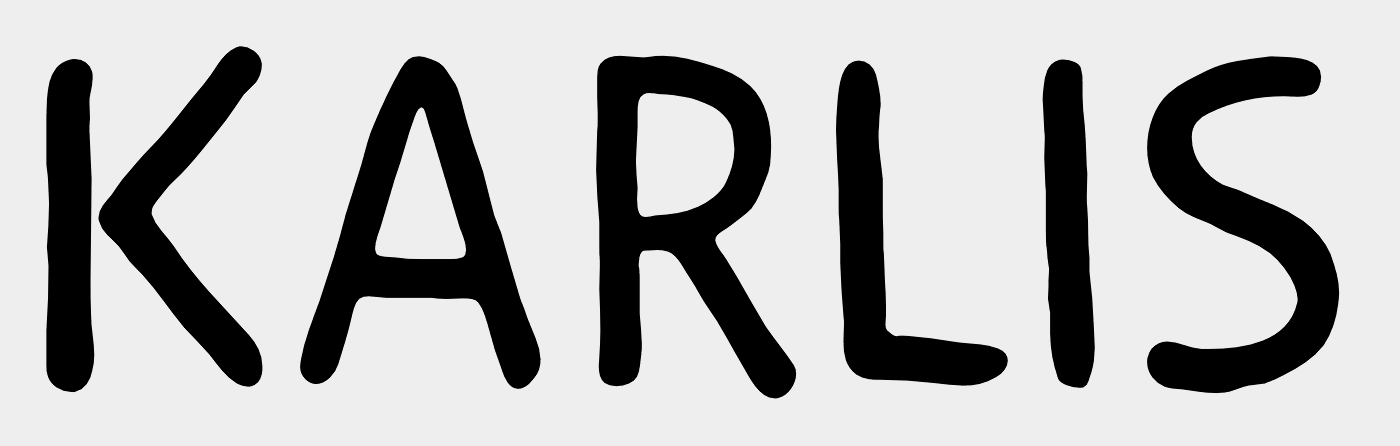
Schrift-Ideen für mein neues Branding gewünscht!
Für mein neues Branding bin ich noch auf der Suche nach einer passenden Typo, die das Gesamtbild harmonisch ergänzt und abrundet. Kurz zu mir: Ich bin Hochzeitsfotograf und in meinem früheren Leben war ich in der Grafikbranche unterwegs, daher auch meine große Liebe zur schönen Schrift. Und somit auch die Qual der Wahl
Die Schrift sollte zeitlos, unaufdringlich und "warm" sein. Gerne hätte ich eine serifenlose Schrift für Headlines und kurze Textpassagen sowie eine Serifenschrift für Fließtext. Letzteres könnte aber auch entfallen, wenn die serifenlose Typo "stark" genug ist, um beide Anwendungsbereiche zu übernehmen.
Meine bisherigen Gedanken gehen in Richtung "Proxima Nova", "Eveleth Clean Thin"…
Anbei findet ihr auch natürlich das dazugehörige Logo!
soll das »KARLIS« im Logo durch die neue Schrift ersetzt werden bzw. ist das Logo schon die Reinzeichnung mit eher »lockerem« Duktus?
Wie auch immer: Die Proxima Nova wäre mir irgendwie zu technisch für das Thema und die Logoidee.
Das Logo ist bereits FINAL und ich suche "nur" noch eine begleitende Schrift für mein CI :-)
Ich persönlich finde die Wortmarke noch nicht ausgereift und vollends zum Stil der Bildmarke passend und würde mir mal Fonts wie die FF Duper (oder breiter laufende) ansehen, die dann auch für die anderen Anwendungszwecke (Headline und evtl. sogar Text) funktionieren.
Es geht nicht um das Logo, sondern um eine Schrift für das gesamt CI! Das Logo ist so fertig.
Merkst Du was? ;-)
Wahrscheinlich hast du recht lange an dem Logo gesessen und die ein oder andere Entscheidung schweren Herzens treffen müssen und willst endlich das Logo stehen lassen. Dennoch würde ich die professionelle Expertise, die dir hier geboten wird nicht einfach übergehen und zumindest in den Details die Schrift im Logo überarbeiten – auch wenn das hier nicht deine Frage war ...
Die Proxima passt tatsächlich wenig zu deiner Beschreibung.
Als Textschrift könntest du dir die Pensum Pro anschauen, die hier letztens vorgestellt wurde :-?
Für eine Sans fällt mir gerade nix ein ...:-(